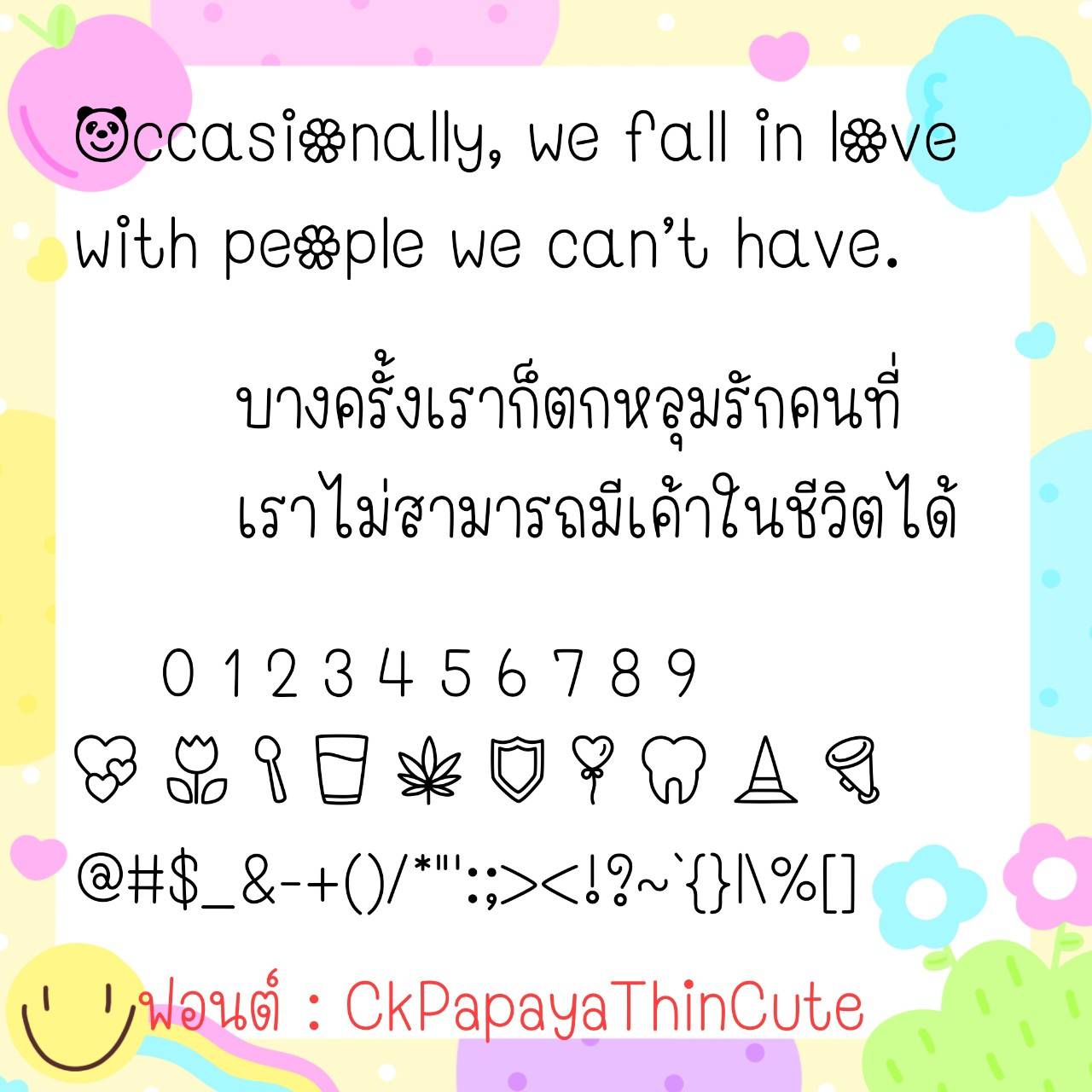
Font CkPapaya
ชื่อสินค้า : Font CkPapaya 💙
🔸 ฟอนต์ลายมือตัวผอมๆสูงๆ เป็นฟอนต์สไตล์วัยรุ่นยุค’90 มีความยุกยิกในตัวนิดหน่อย ดูไม่น่าเบื่อ และยังมีไฟล์อิโมจิน่ารักๆ ที่ใช้ปืนเลขไทยให้ด้วยค่ะ 🥰💙
🔹 Tall, thin handwritten fonts are a 90s teenage style font with a bit of wiggle in them, so they don’t look boring. There are also cute emoji files that use Thai numerals. 🥰💙